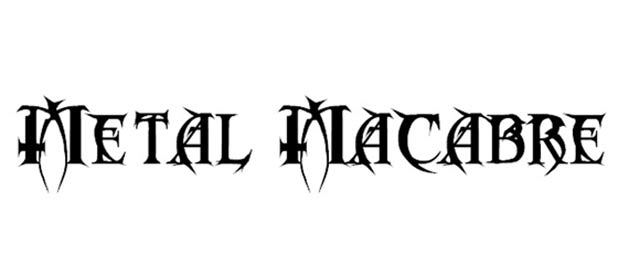
今天,小编@Iamkikidong 带来的是35款另类的哥特式字体。你可以用很多形容词来描述它们:经典、艺术、怪诞、神秘甚至脏兮兮!但这些都抵挡不住它给你的作品蒙上一层黑暗复古的魅力!有需要的童鞋赶紧下手哦!
Gothical
Indoctrine
Rapscallion
spooky-magic
Drawn Old English
Creepygirl
Waters Gothic
MKantzley
GothicHandDirty Font
Gothic Love Letters
Strassburg Fraktur
Vtks Relaxing Blaze Font
Flying Hollander
Quael Gothic
Cuxhaven Times
Metal Macabre
Cold Night for Alligators
Cardinal
Vtks espinhuda
SF Gothican Font
1456 Gutenberg
Shlop Font Family
Sharp 2.0 Font
Bloodsuckers
Blood Of DraculaSW Font
Feast of Flesh
A Gothique Time
Bill Hicks
Dissonant Font
Augusta
Memela Fraktur
Black Castle
Proclamate
Fiddums Family
Cartographer